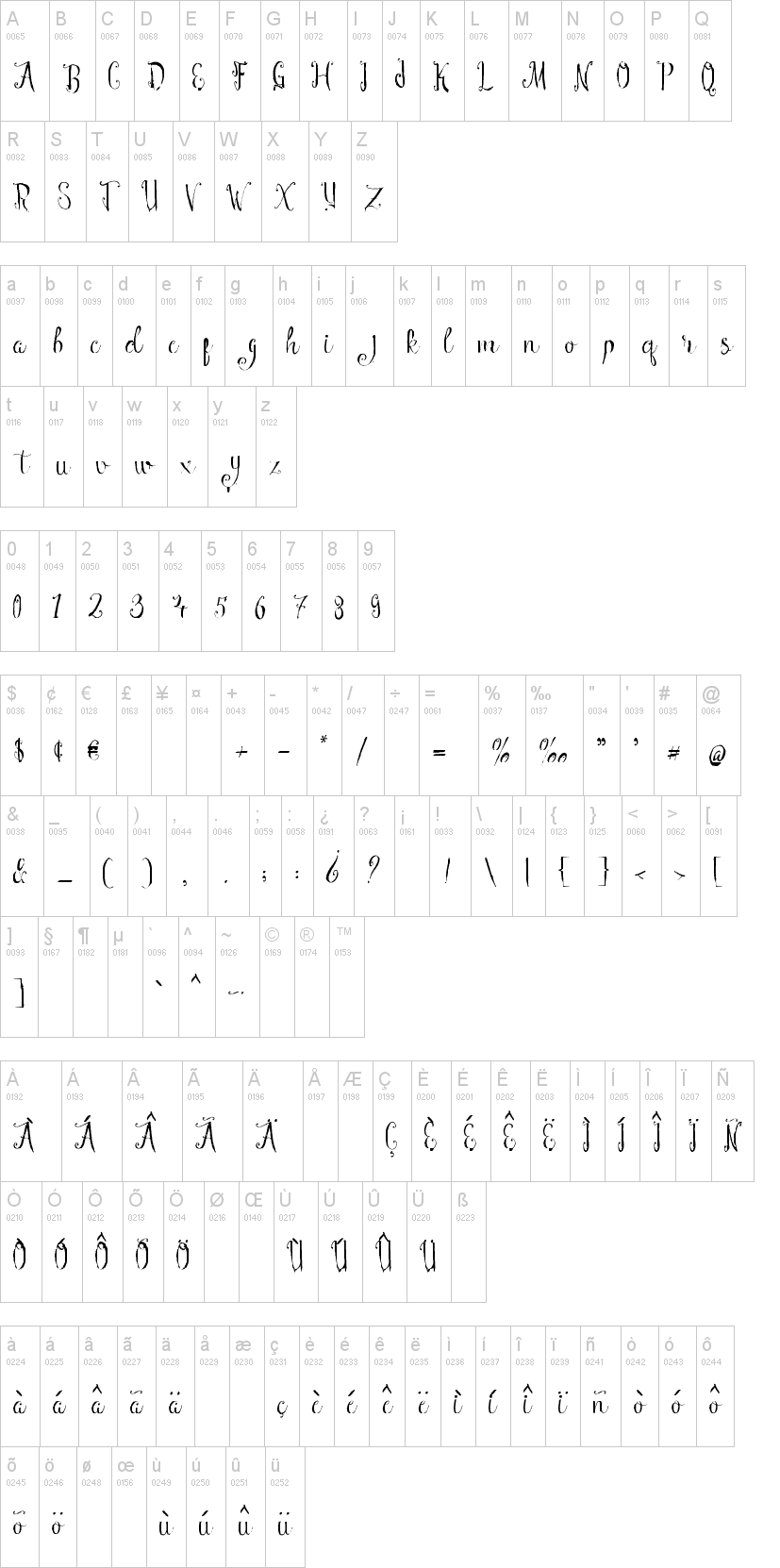
Manny Script 是一款漂亮的手写体字体,它具有柔和的线条和温暖的色彩,能够带来温暖舒适的感觉。Manny Script 字体的文字结构清晰,笔画流畅,字形细腻,更具有一种温暖的自然触感。它的设计充满活力,既可以用来制作海报,也可以用于网页设计、T恤印刷和其他印刷品。内容介绍
Manny Script是一款非常不错的手写艺术字体,具有很好的视觉感,适合于文化类的宣传设计、商业类品牌的广告和产品包装设计以及个性化文字排版等较多场景。